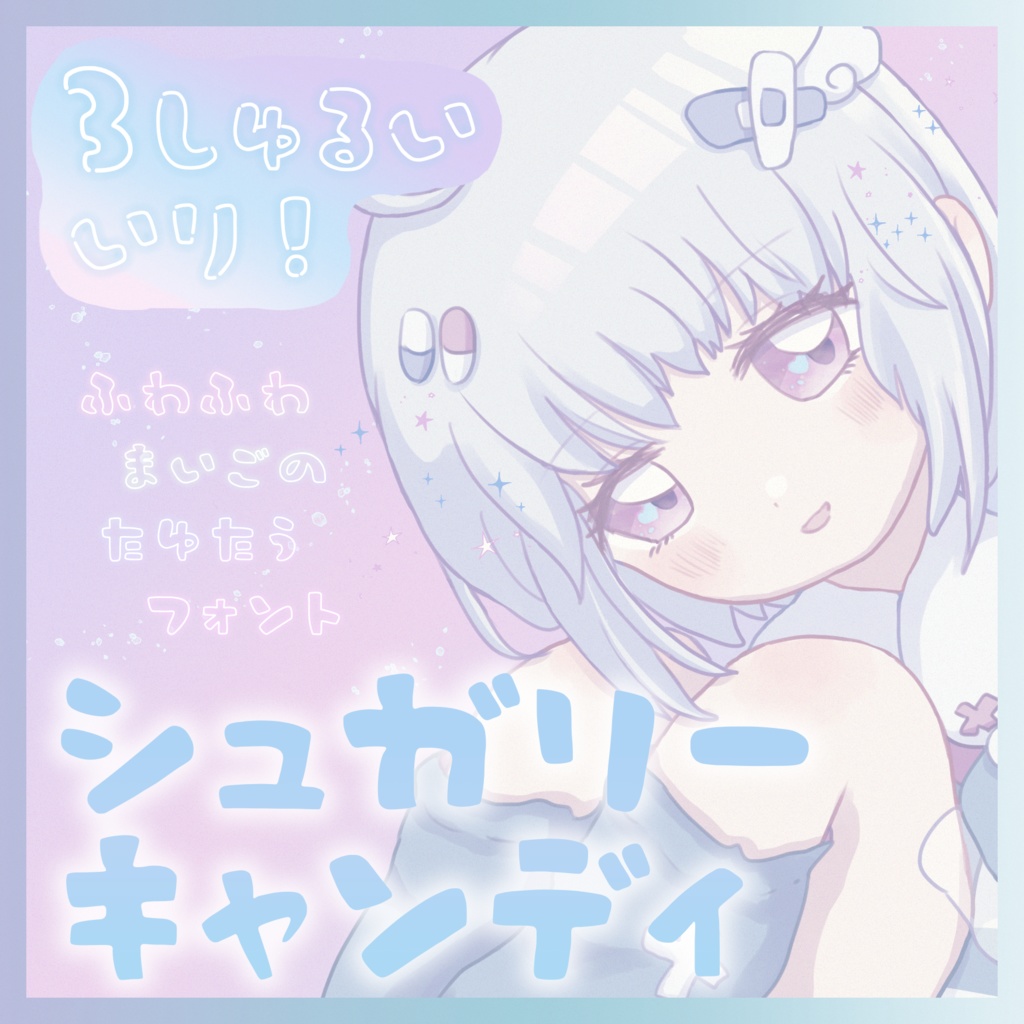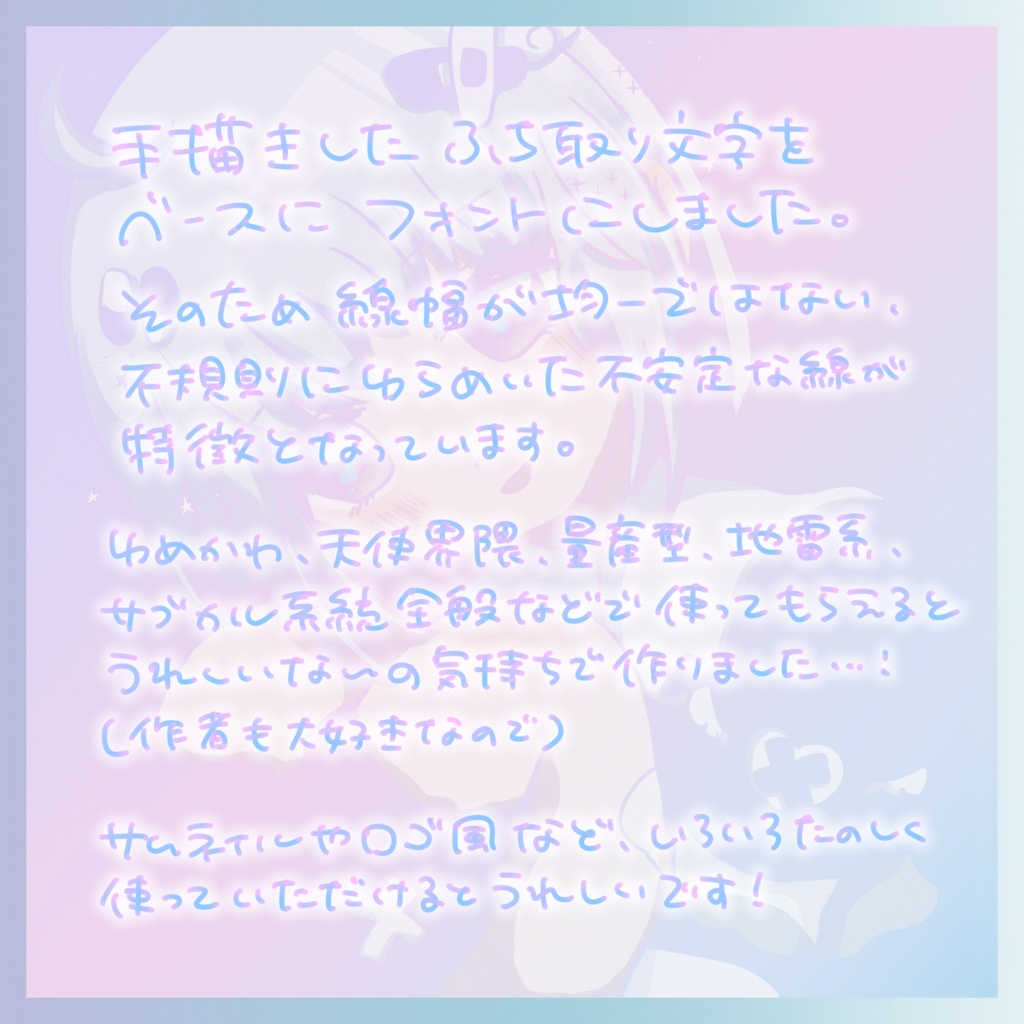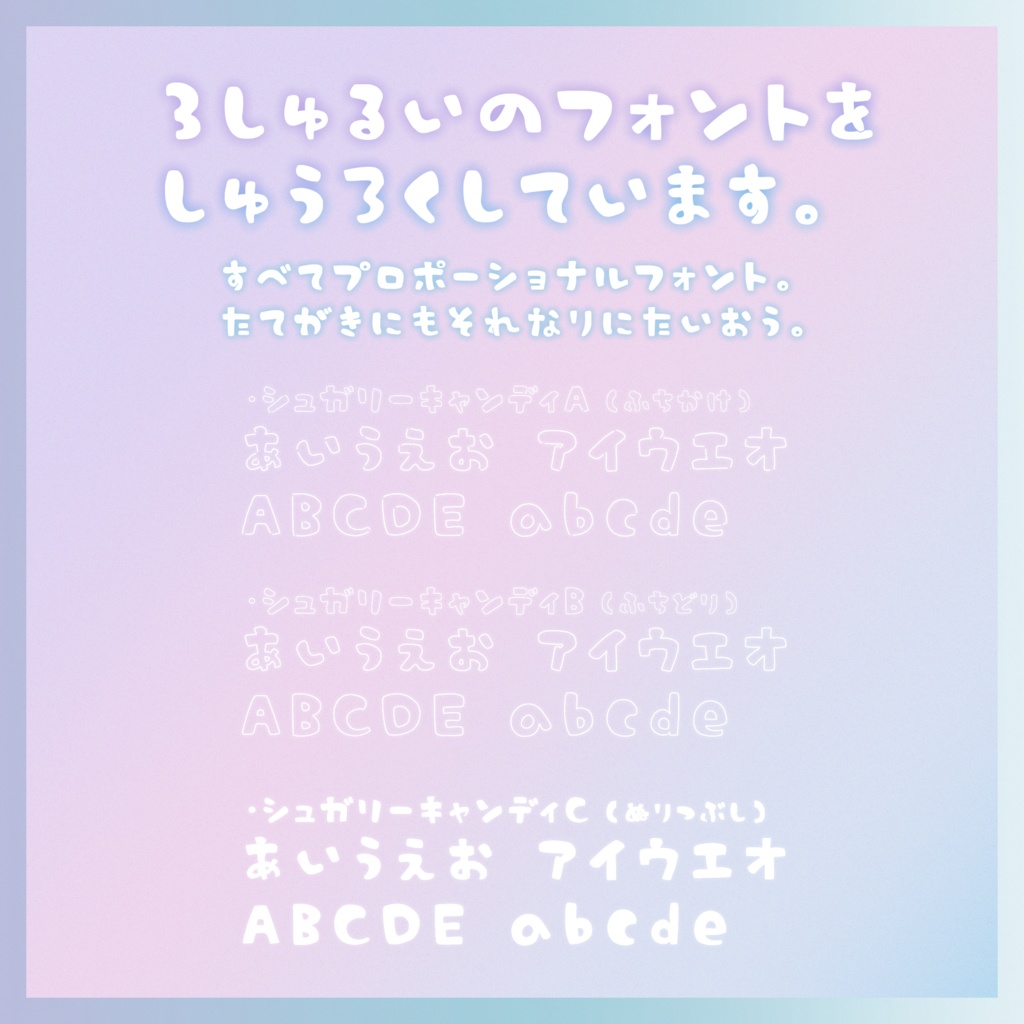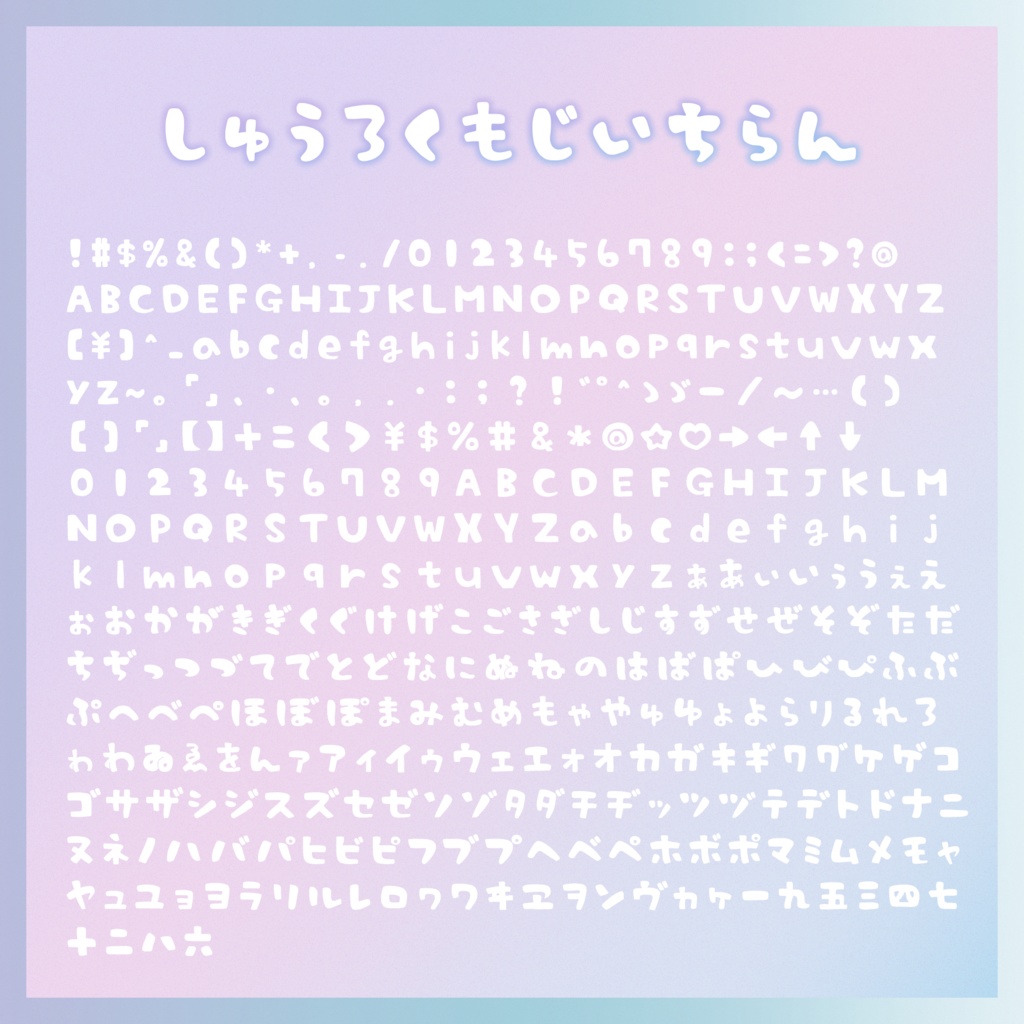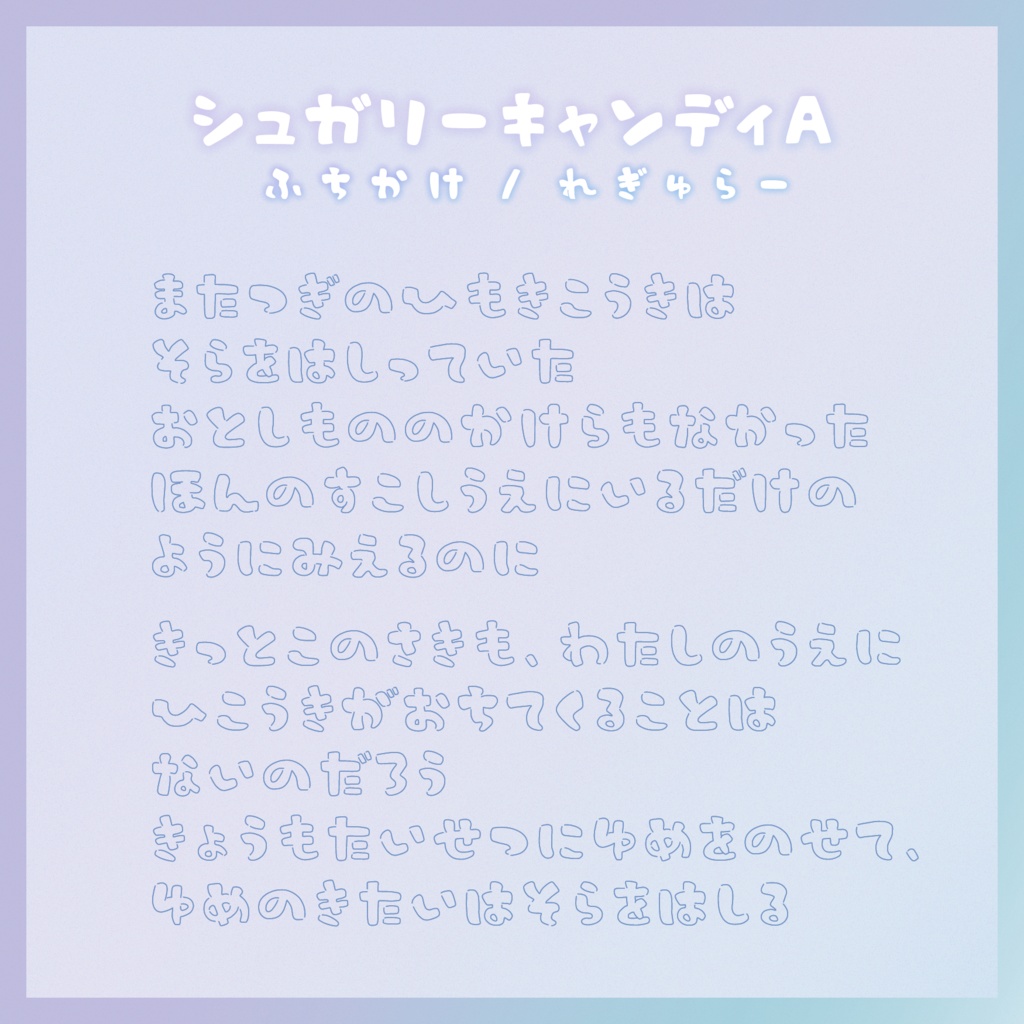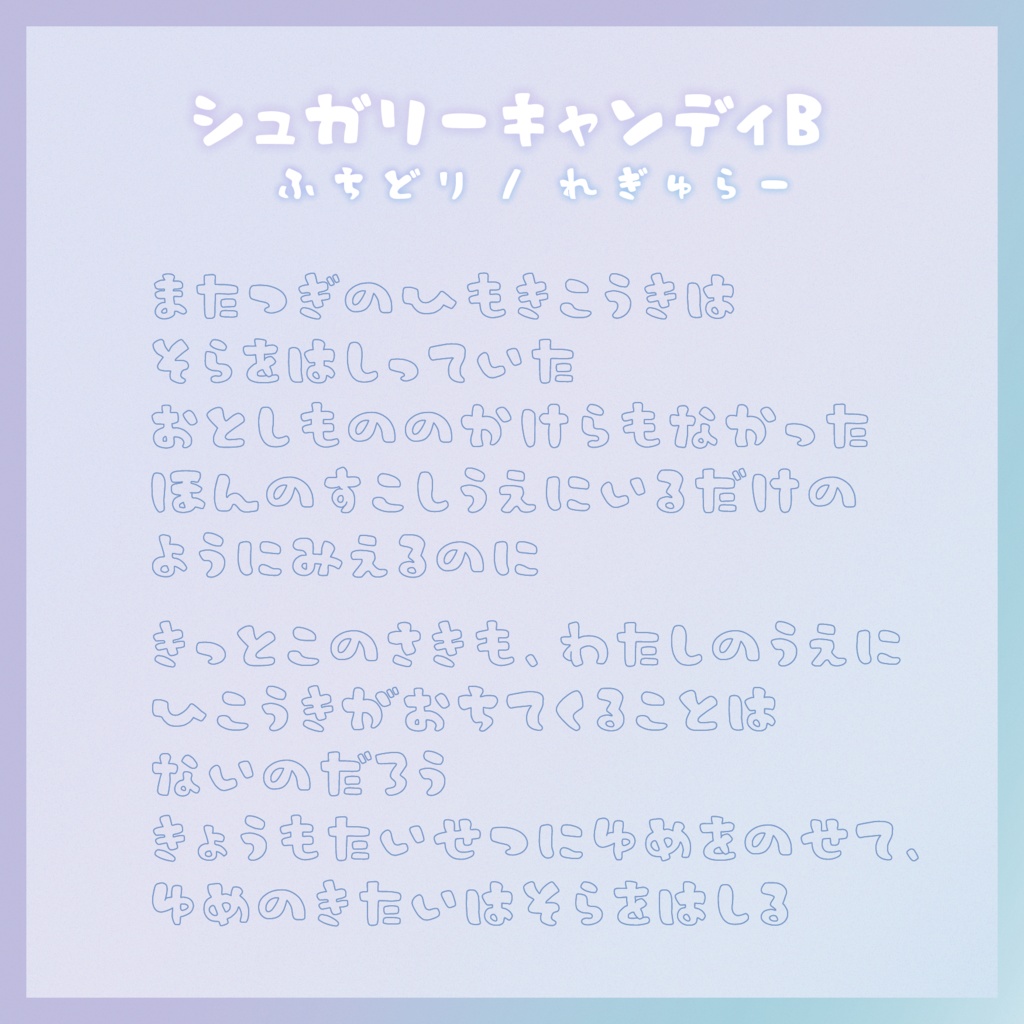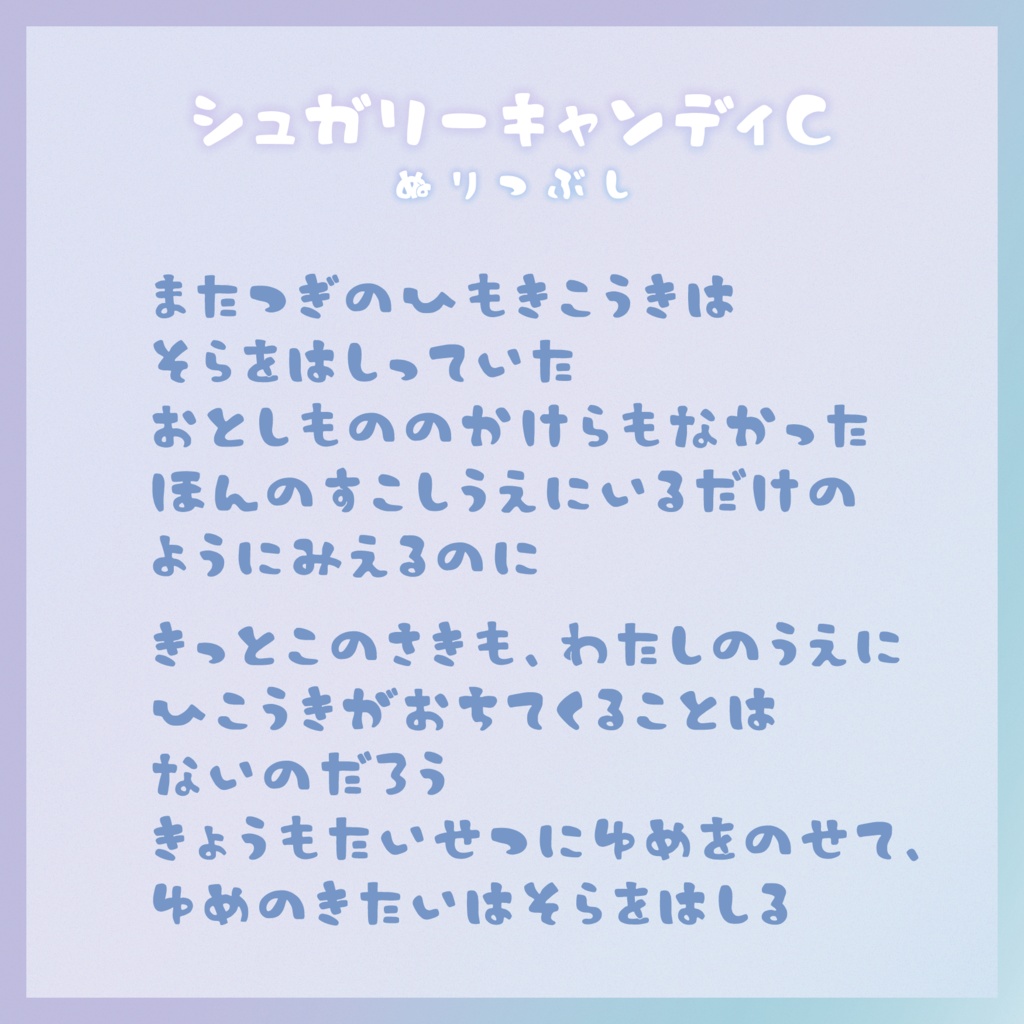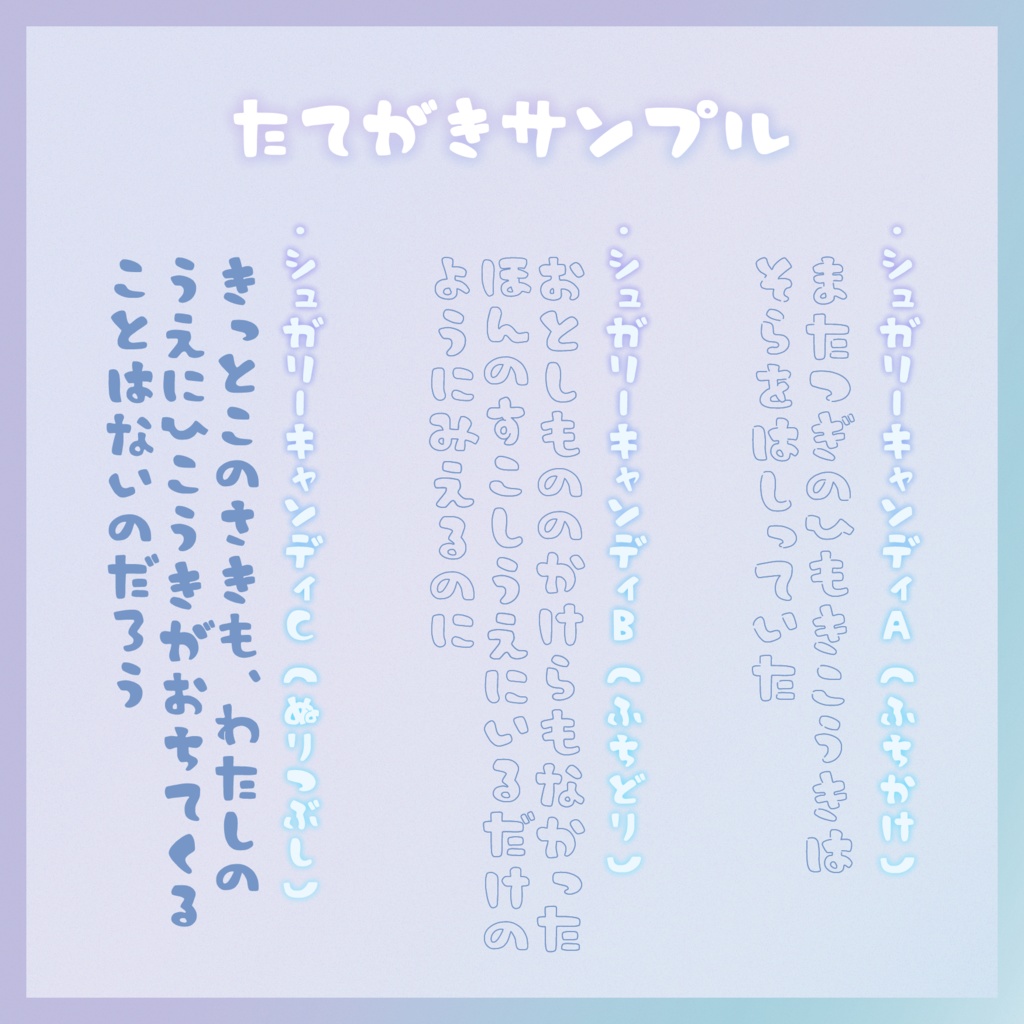
こちらのフリー版は【 商用利用禁止 】です。 商用でのご使用には商用版ライセンスをご購入ください。 DL前に必ず下記URL先より利用規約のご確認をお願いいたします。 https://berrymilksugar.com/font/ ---------------- ふわふわまいごのたゆたうフォント こころのすきまが埋まらないあなたへ 手書きした縁取り文字をベースにフォントを作りました。 そのため、線幅が均一ではない 不規則に揺らめいた不安定な線が特徴となっています。 ゆめかわ、天使界隈、量産型、地雷系、サブカル系統全般などで使いやすい文字を目指しました。 フリー版では3種類を収録しており、組み合わせ次第で様々な使い方ができるかと思いますので、ぜひ楽しんでご使用いただけますと幸いです。 ・OpenType、TrueType形式 / プロポーショナルフォント / macOS 15.6.1、Windows11にて動作確認済み ・収録文字はひらがな、カタカナ、英数字、各種記号、漢数字 合計 377文字 ・今後不定期にアップデートの可能性あり ---------------- 【投げ銭版】(追加文字のリクエストを受け付けています。) https://berry-milk-sugar.booth.pm/items/7629135 【商用版】 https://berry-milk-sugar.booth.pm/items/7629162 もあります。 お気に召しましたら、なにとぞよろしくお願いいたします。 SNS等でのシェアもとても励みになります……!